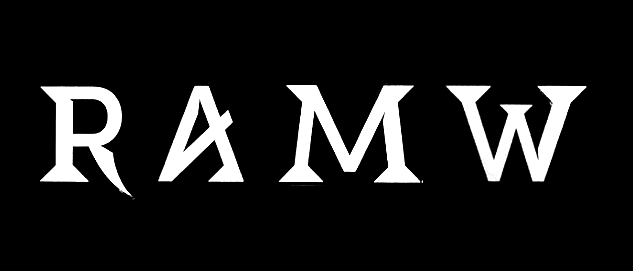
Suche Schrift mit markantem R
habe folgende Schrift auf einem Plakat im Netz gefunden. Kann mir jemand sagen um welche es sich handelt. Sämtliche Suchmaschinen habe ich schon befragt. Ich denke die Schrift kommt von einer kleineren, eher unbekannten, Foundry.
Oder jemand hat einfach nur die paar Buchstaben gezeichnet. Schließlich muss ein Schriftgestalter das ja auch machen, nur eben deutlich mehr Schriftzeichen, bei denen er dann noch aufpassen muss, das auch alle, und nicht nur eine Hand voll zusammen passen.
Warum also muss alles, was Buchstaben sind einem Font entstammen?
Muss nicht, kann aber. Deshalb auch die Frage. Ich bin mir ziemlich sicher, dass es zumindest eine ähnliche Schrift gibt.